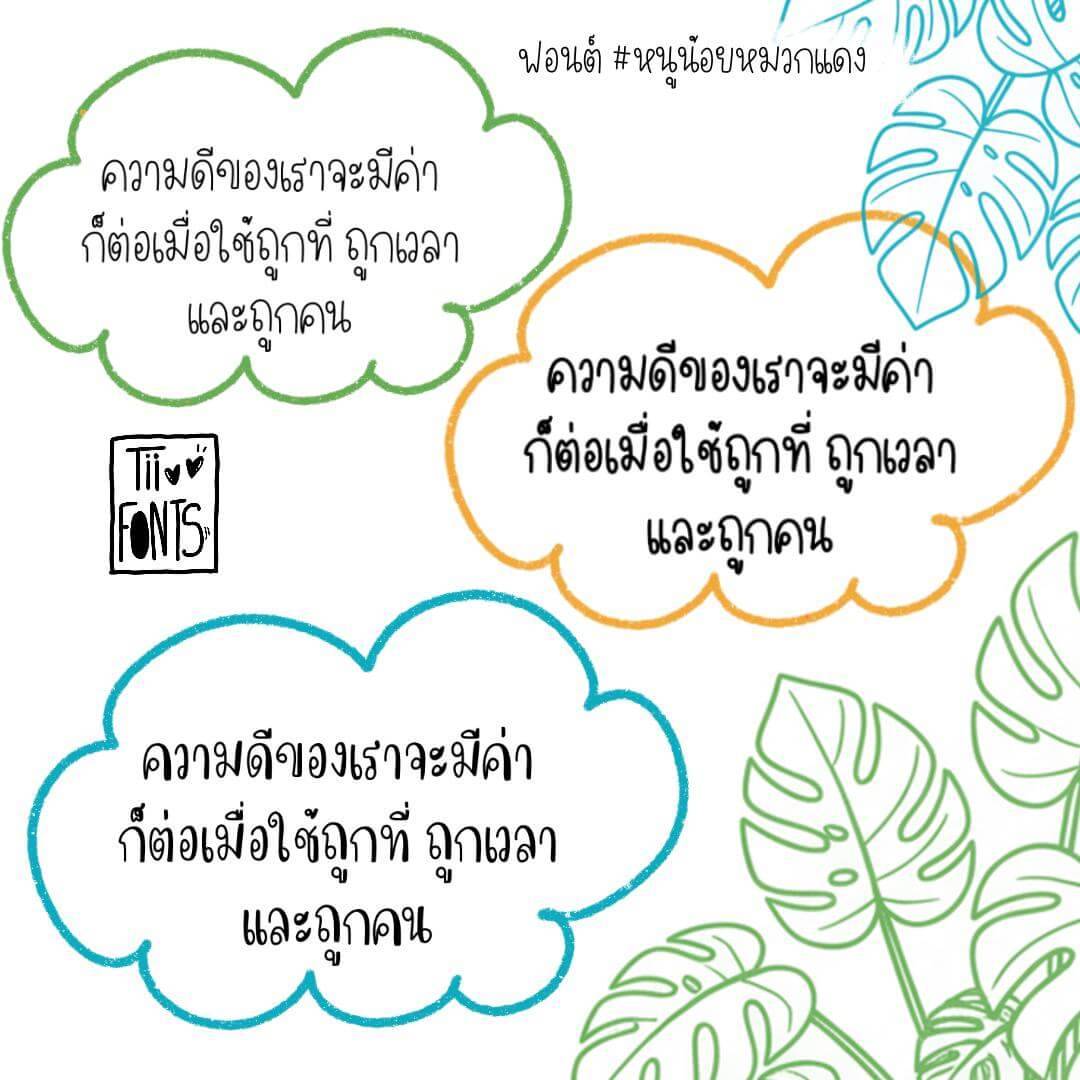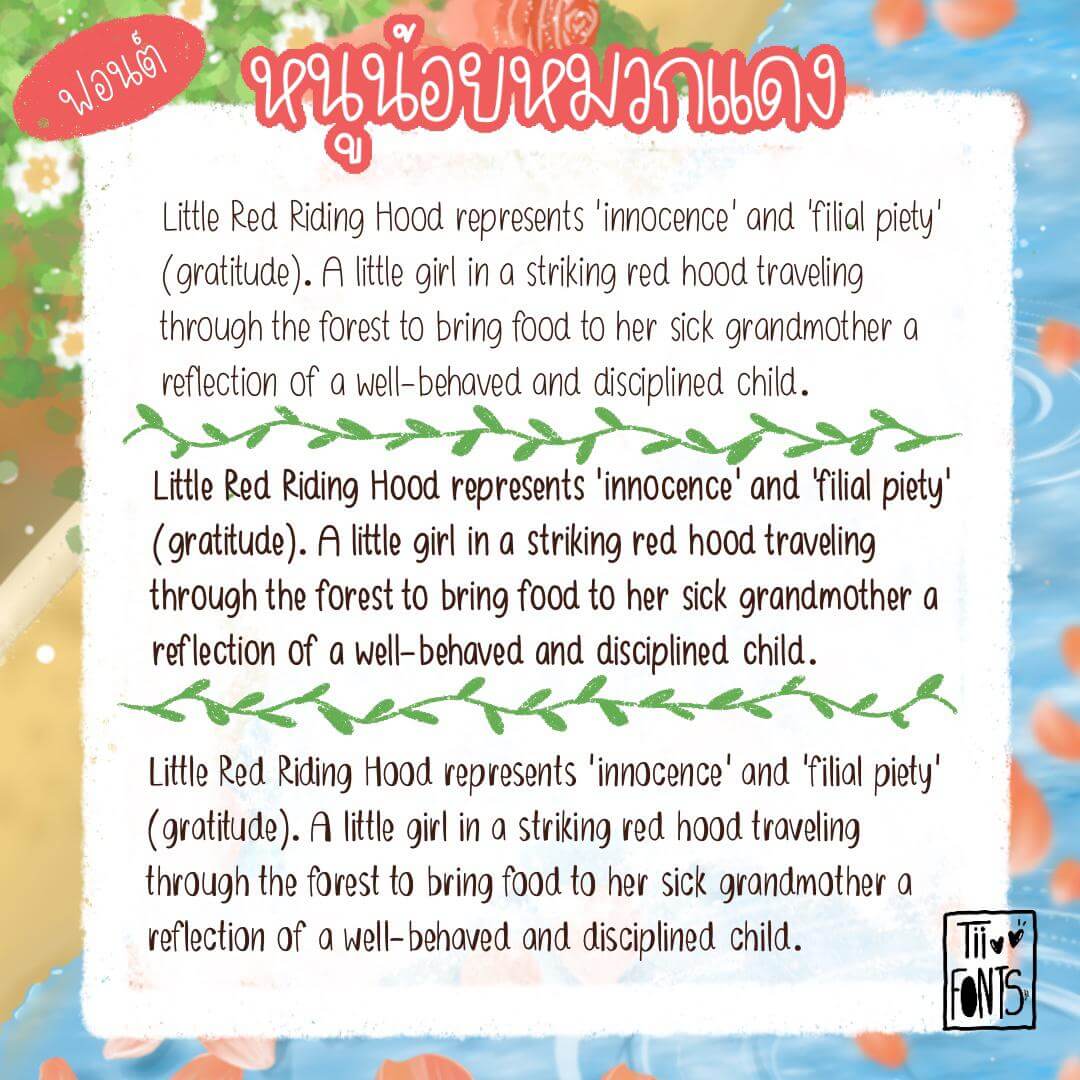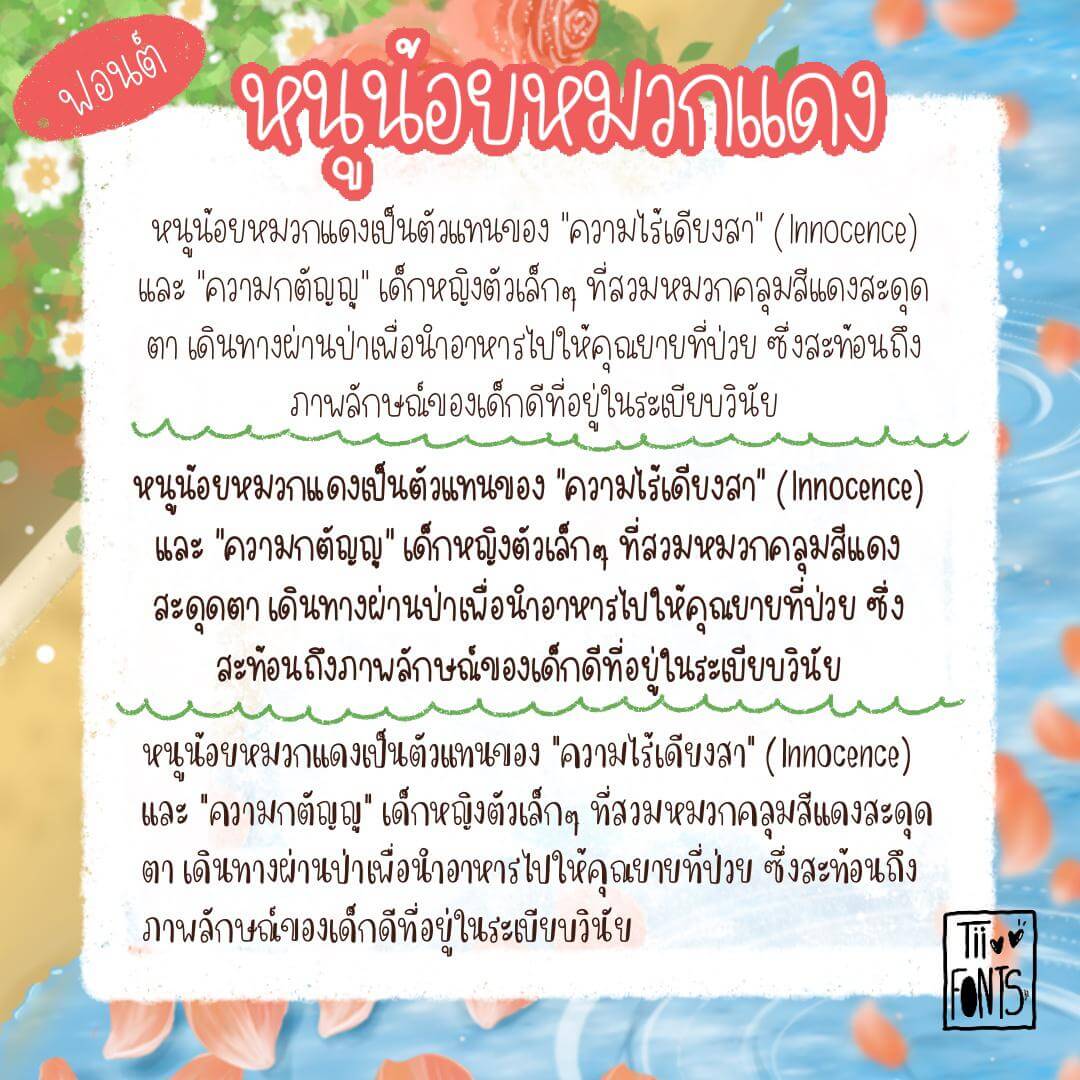
หนูน้อยหมวกแดง (TTALittleRedRidingHood)
เติมความละมุนให้งานเขียนของคุณ ✨ สายจดสรุป สายทำคอนเทนต์ ห้ามพลาด! กับฟอนต์ลายมือสุดคิวท์ที่มีให้เลือกถึง 3 สไตล์ในเซ็ตเดียว ไม่ว่าจะเขียนหัวข้อเก๋ๆ หรือจดเนื้อหาแน่นๆ ก็เอาอยู่
ทำไมต้องมีฟอนต์หนูน้อยหมวกแดง?
• ดีไซน์ละมุนตา: ตัวอักษรมีความเป็นระยิบระยับและเป็นระเบียบในเวลาเดียวกัน
• 3 หัวปากกา: เลือกใช้ได้ตามความเหมาะสม ทั้งแบบหัวเล็กเรียบง่าย หรือหัวอวบอิ่มเน้นข้อความ
• อ่านง่ายสุดๆ: ออกแบบมาให้มีหัวชัดเจน จะจดโน้ตสรุปบทเรียน หรือแต่งสตอรี่ IG ก็ดูดี